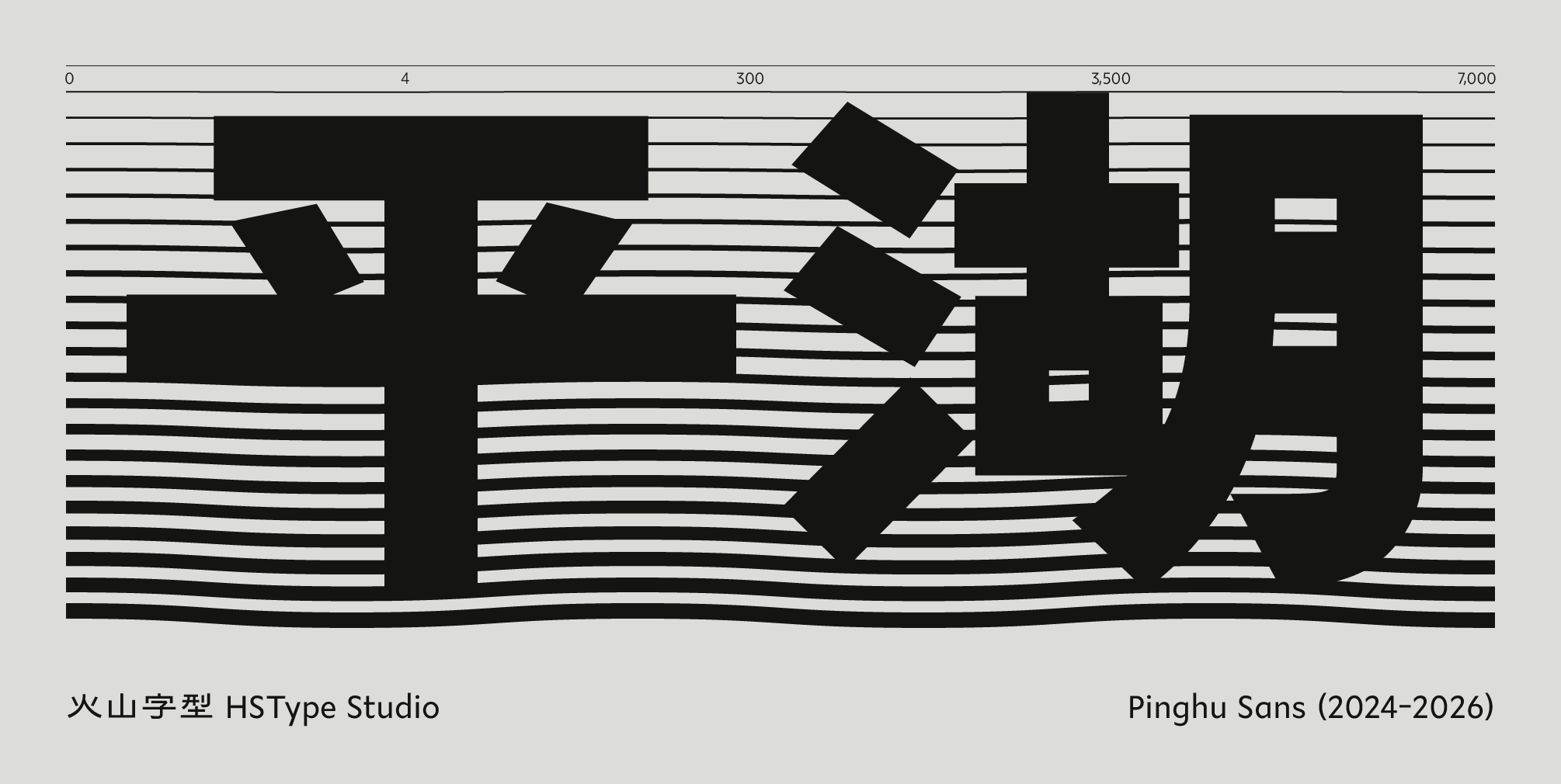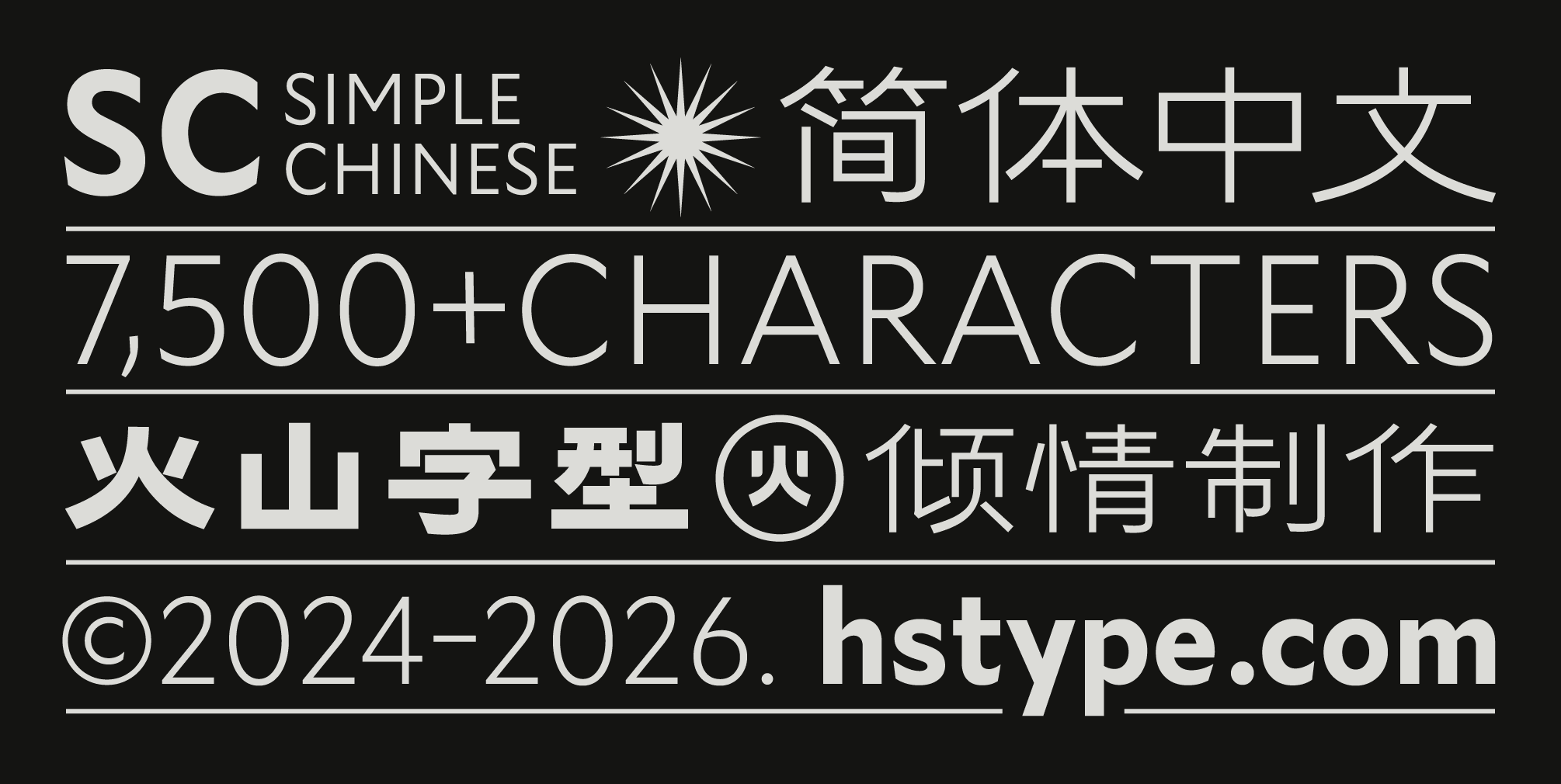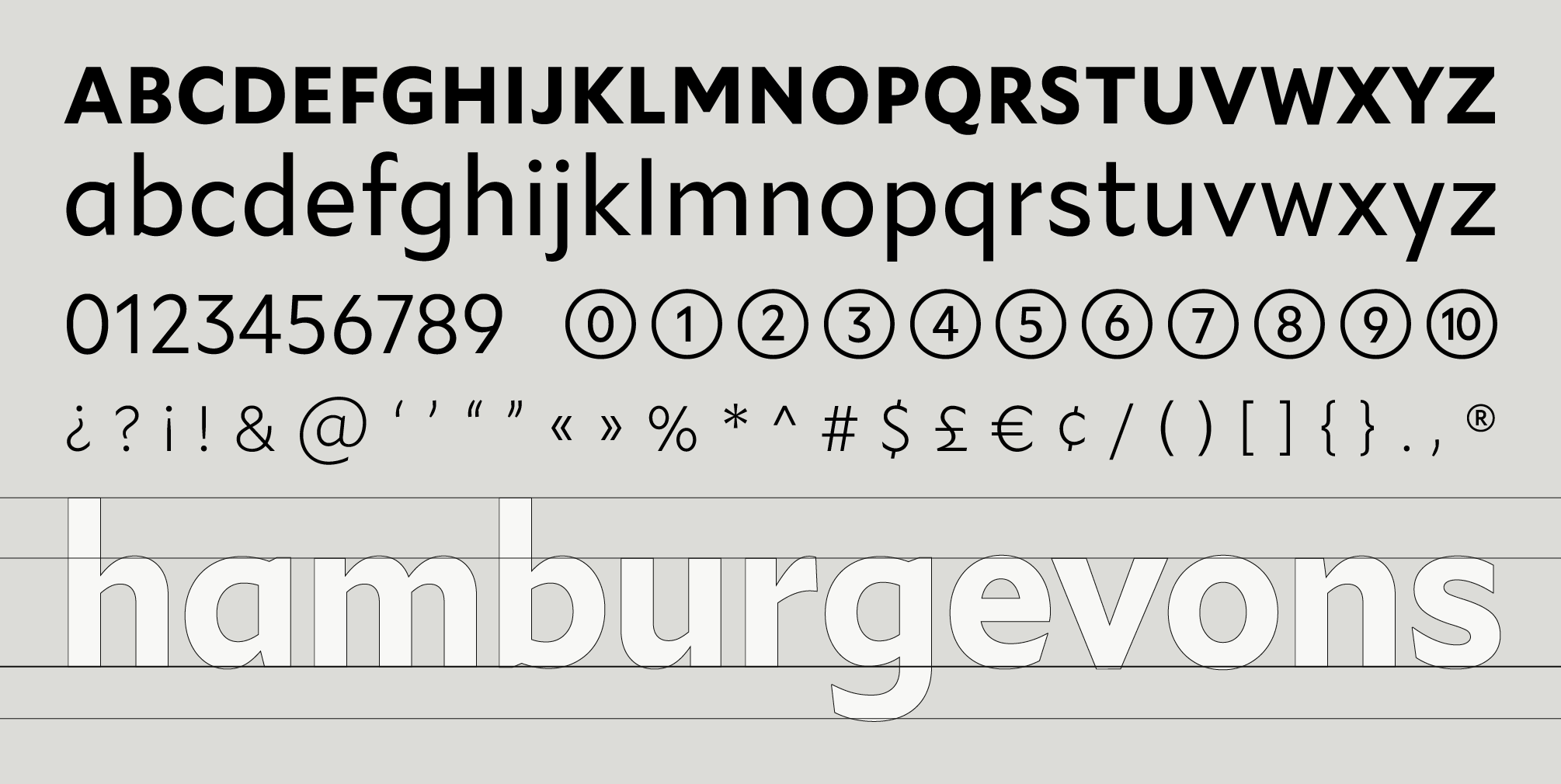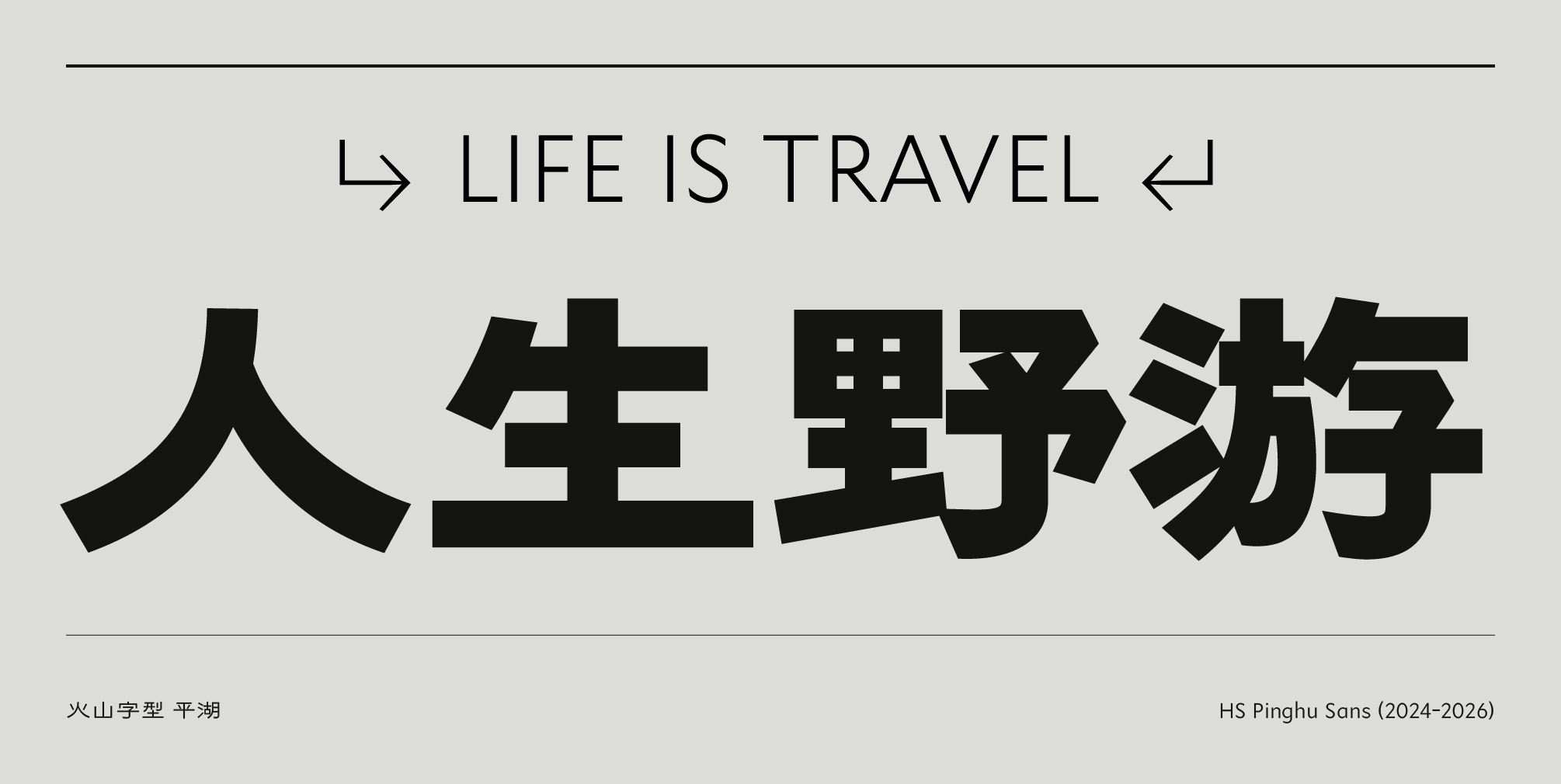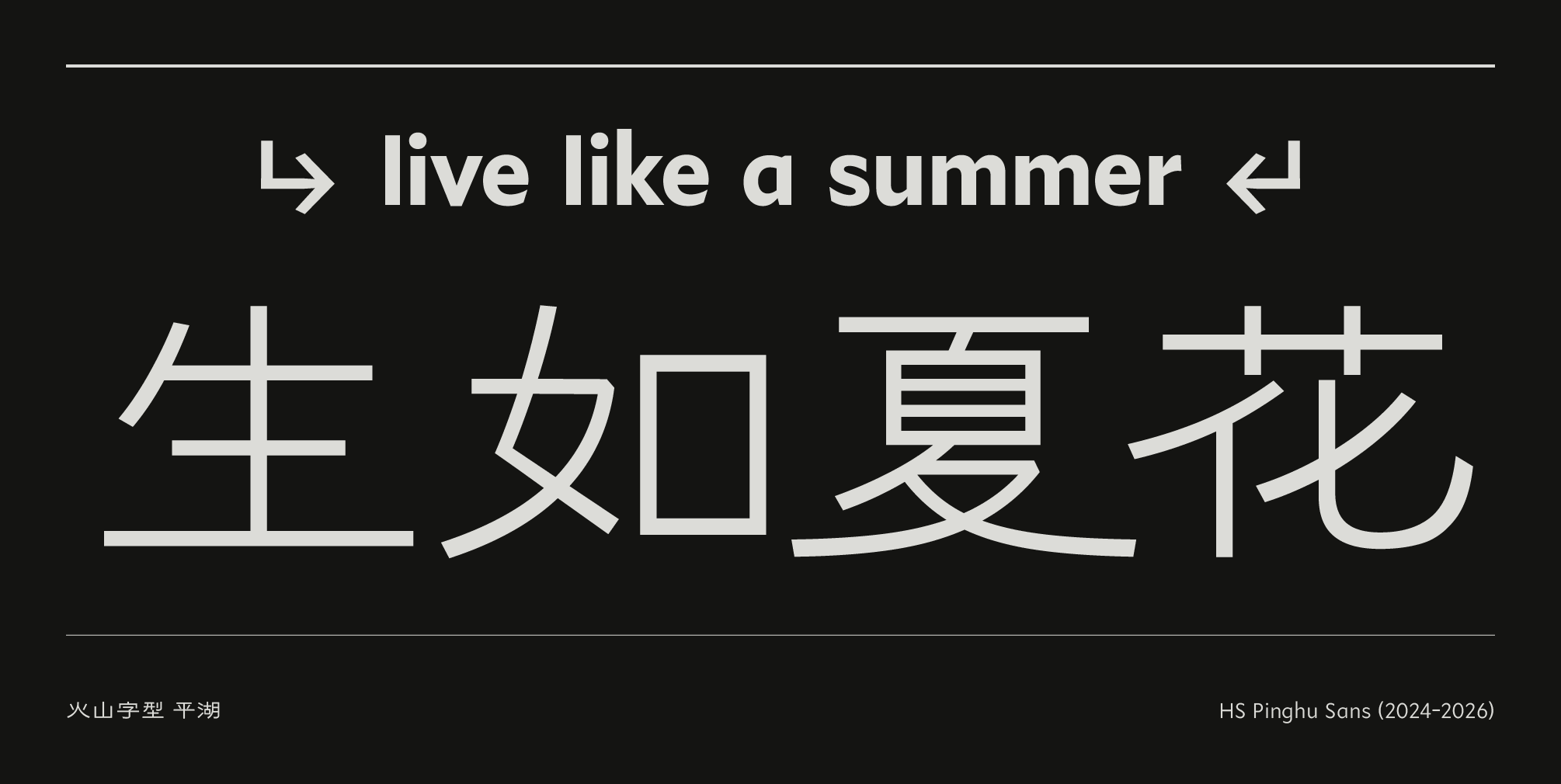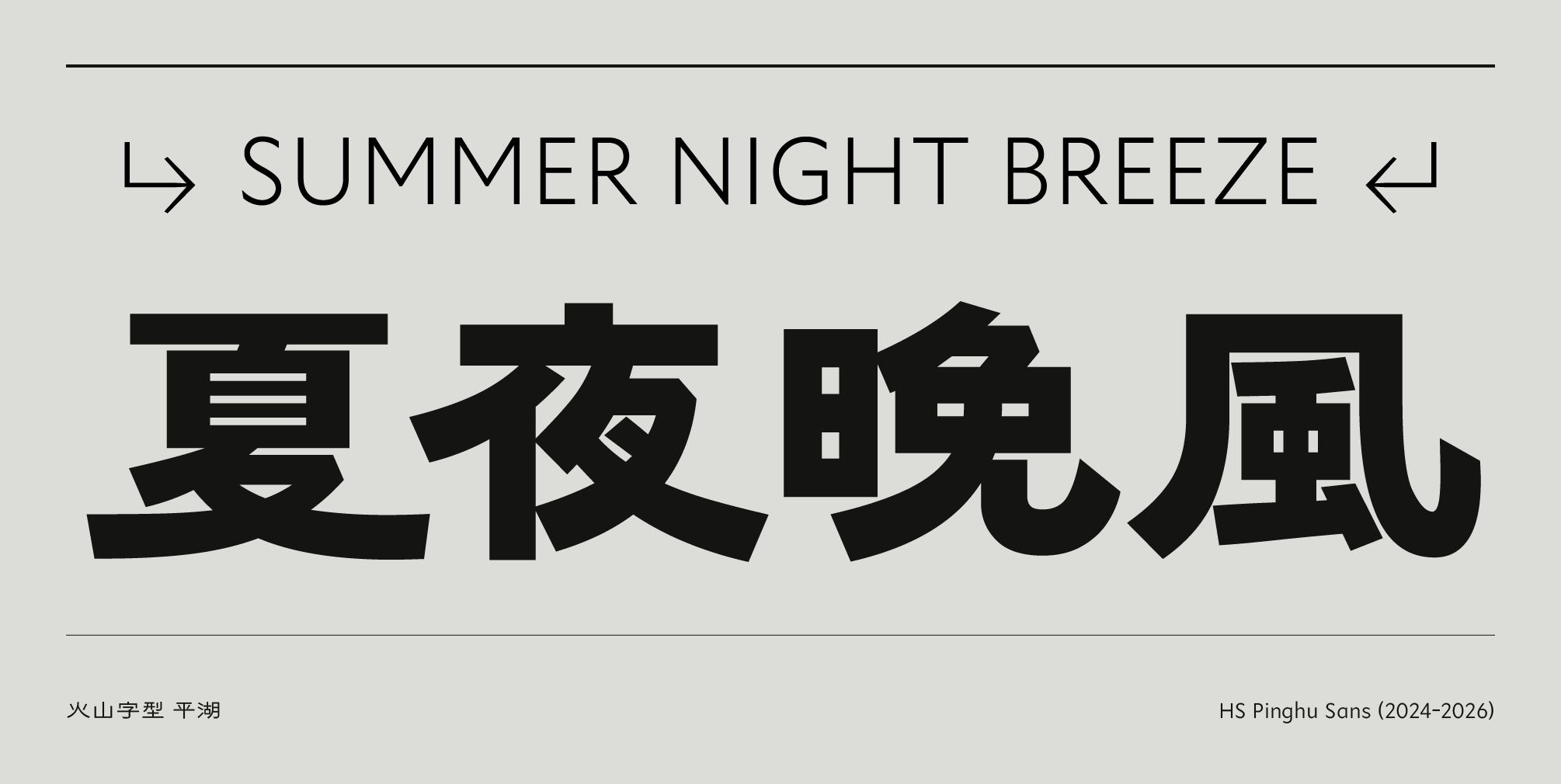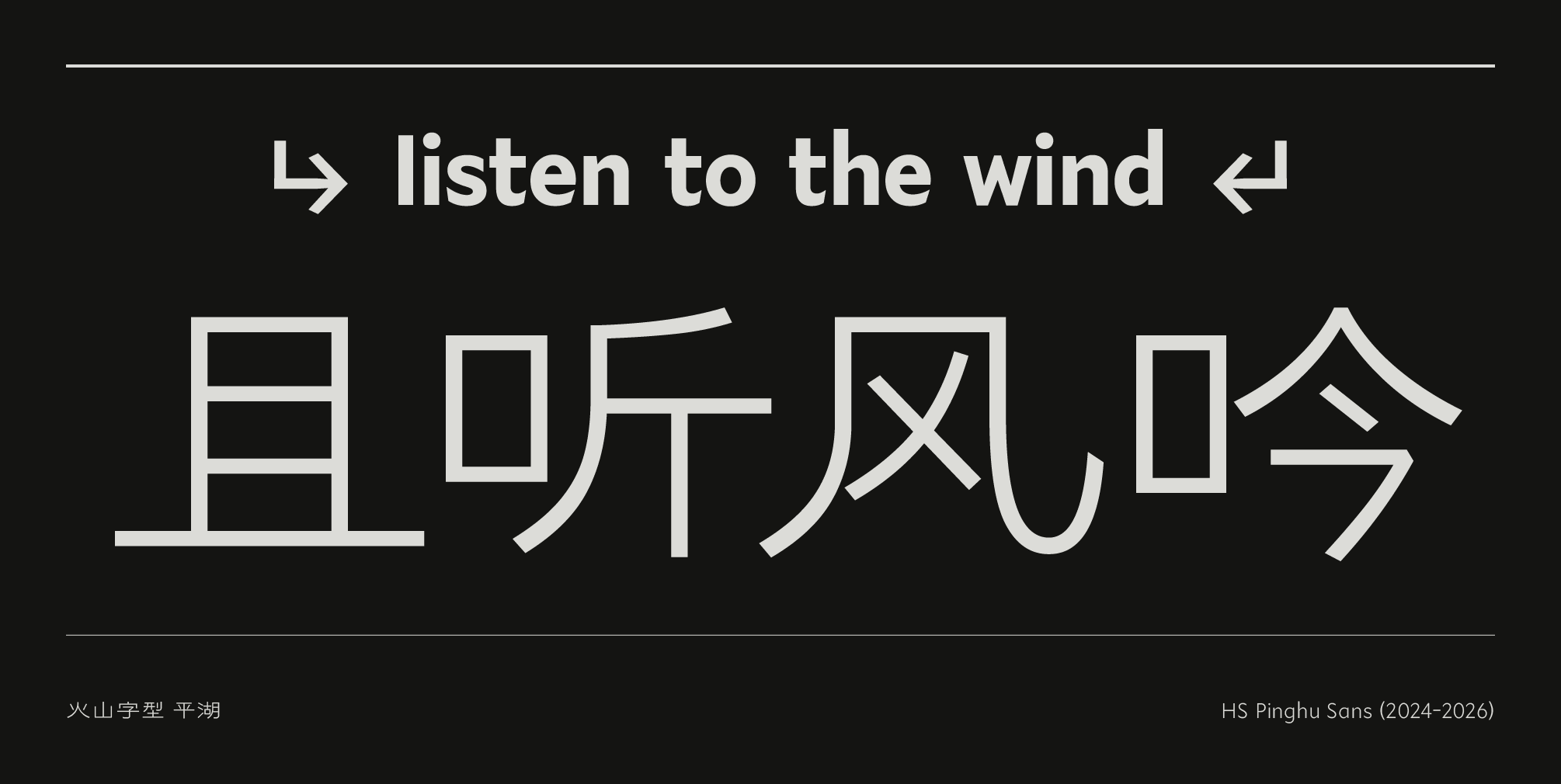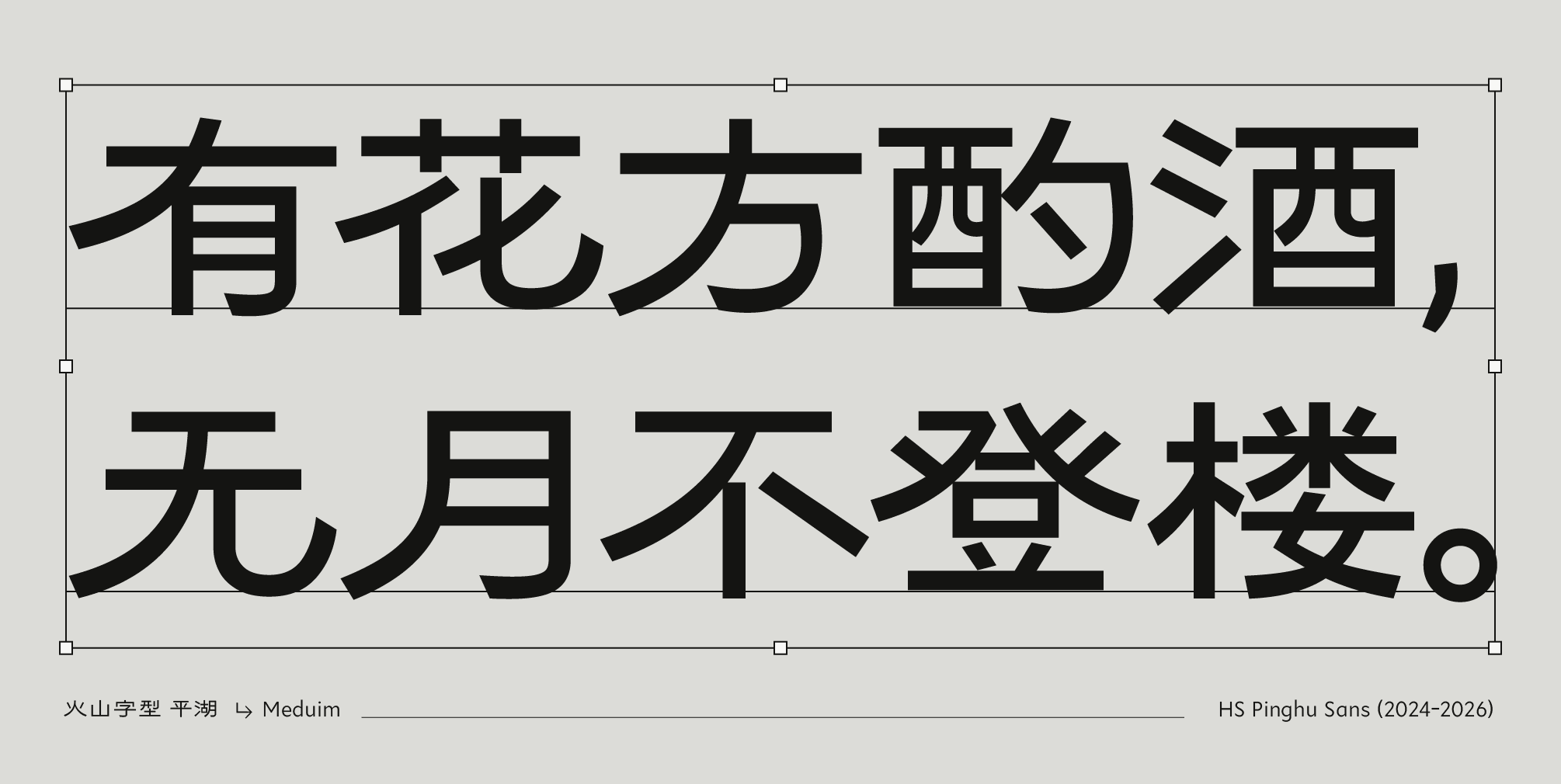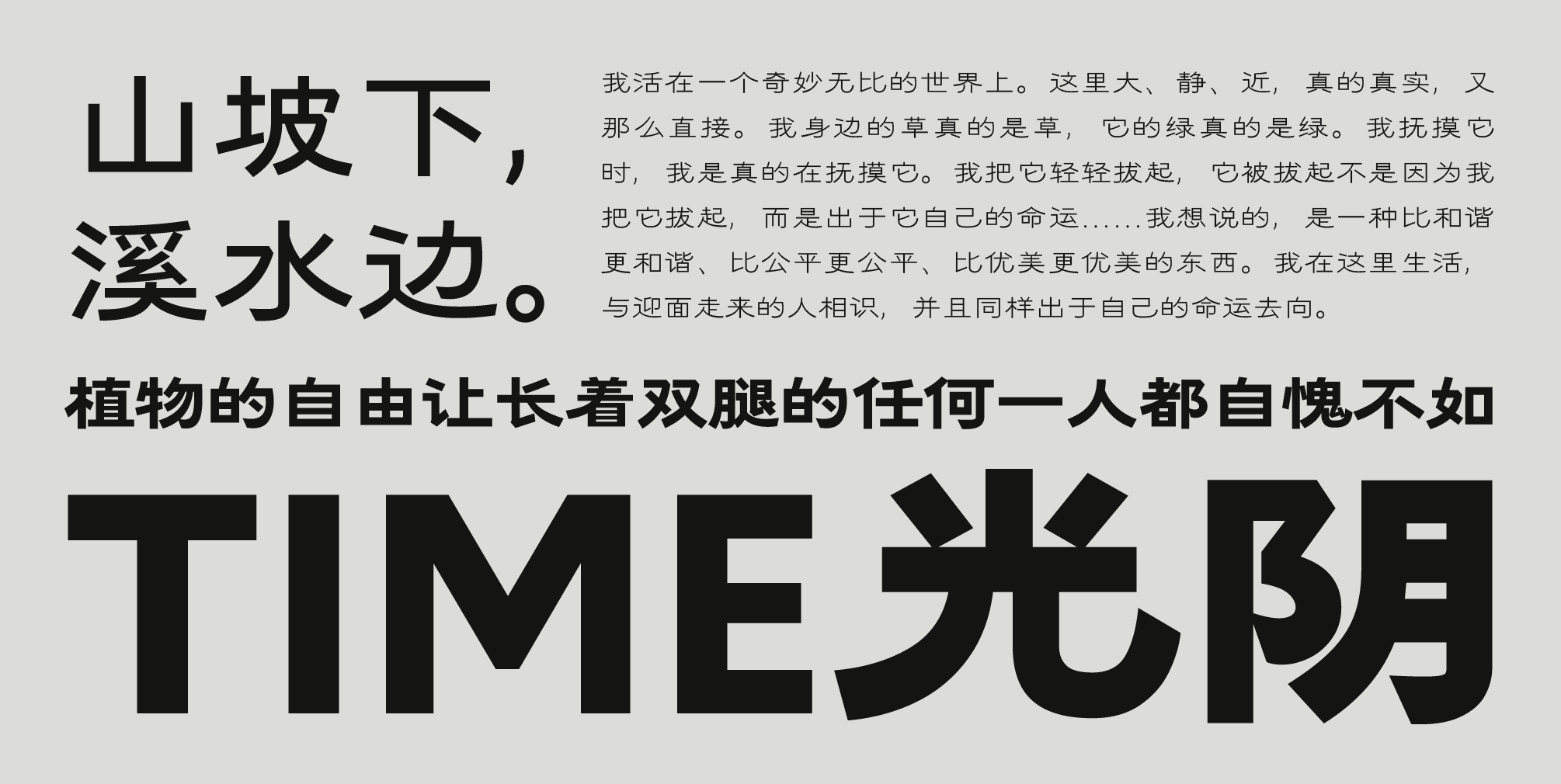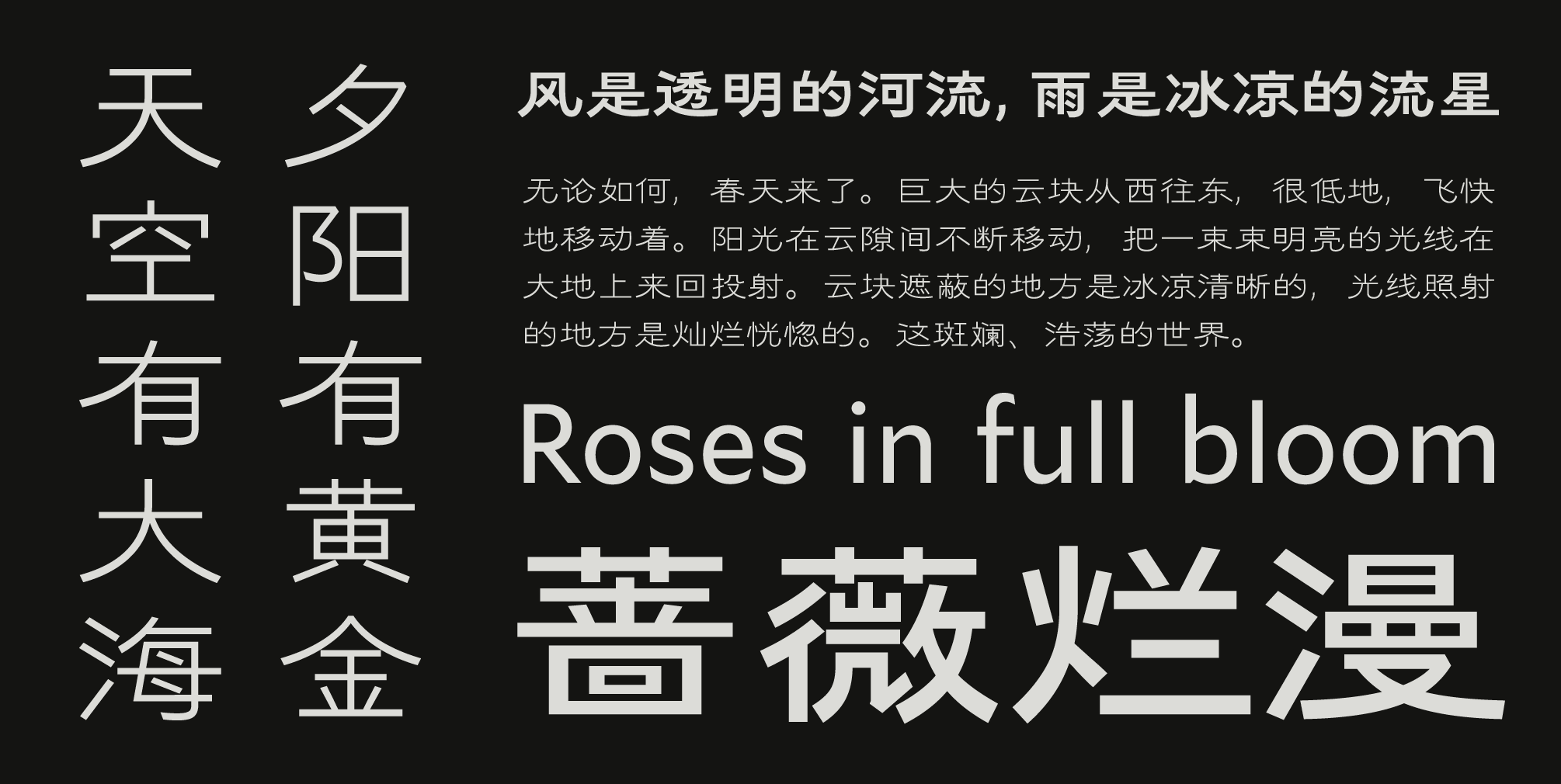
火山字型 平湖 (6字重)
“火山字型 平湖”是对黑体的一种独特探索,它不仅仅是“汉字黑体的另一种可能性”,更是一种具有人文气息、富有韵律的黑体风格。
平湖的笔势和结构借鉴了汉隶的主要特征:字面扁方、中宫紧收、结体舒展。区别于其他“人文黑体”的做法,平湖的笔形设计是极简的几何结构,没有装饰性或风格化的处理。结体生动多变、富有张力,每个文字都聚散自然、主次有度,同时又保持了设计目标的全局稳定和风格统一。这种“几何+人文”结构为“平湖黑体”在表达性与实用性之间找到了精准的平衡点,而强烈的书写感则增添了温暖的质感,为当代设计表达带来一种柔和宁静的秩序感。
“平湖黑体”提供6个字重,使其能够胜任各种应用场景:广告、包装、品牌推广、阅读和界面设计…… 为设计师提供了灵活的创作空间,同时又不失一致性。